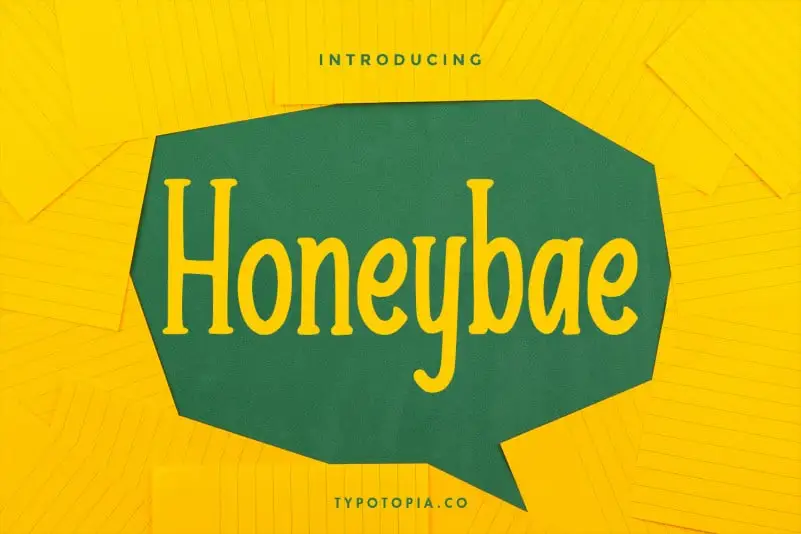
Honeybae – Fun Display Font – Download Grátis
Introduzimos Honeybae, uma fonte de exibição divertida e única. Esta opção de estilo é perfeita para adicionar vida e personalidade a qualquer projeto visual. Feita pelo designer typotopia, esta fonte oferece um toque diferente que certamente irá chamar atenção em sua próxima criação gráfica. Perfeito para headlines, banners ou qualquer outro elemento que precisa destacar-se na tela, Honeybae é uma escolha inteligente tanto para designers digitais quanto para profissionais de design gráfico. Com seus traços exagerados e cores vibrantes, esta fonte de estilo grande não só enriquecerá a sua composição visual, como também ajudará a transmitir seu lema ou mensagem com força.